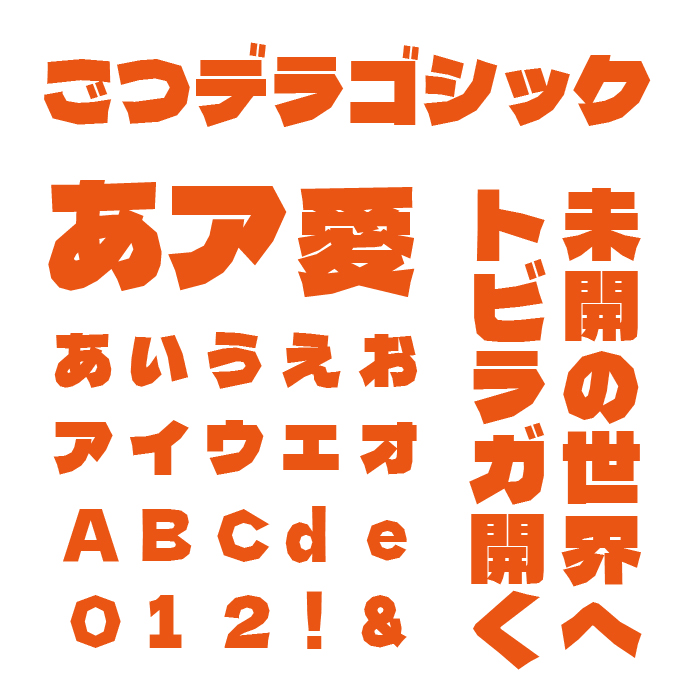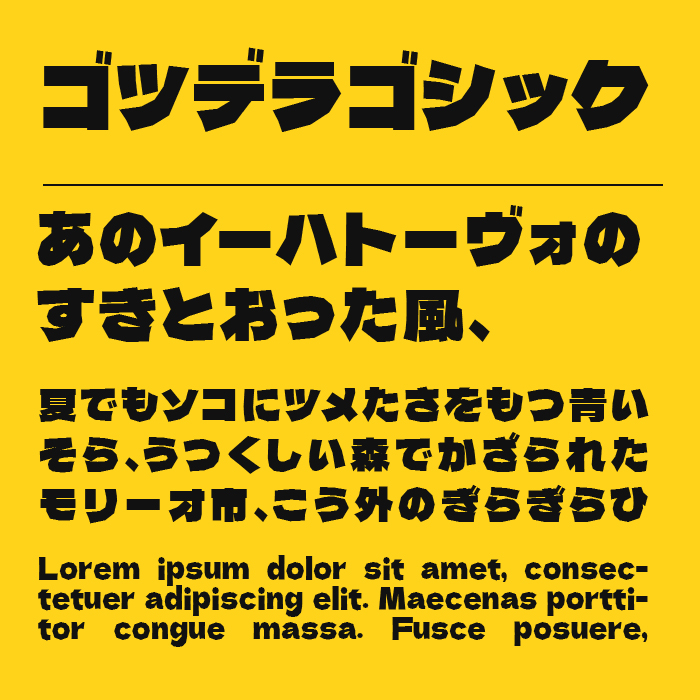
ゴツデラゴシックフォントは、その名のとおり「ごつさ」が魅力の超極太ゴシック体です。
デラゴシックフォントをベースとして、ゴツゴツになるように加工が施されています。ポップだけど。インパクトがあり力強く、メッセージを力強く届けたいときにぴったりです。
タイトルやロゴ、イベント告知など、目を引きたいとき場面などで取り入れると効果的に発揮する力強さと親しみやすさが両立しており、エンタメ系や子ども向けにもぴったりなフォントです。
収録文字は、漢字・ひらがな・カタカナ・アルファベット・数字・記号が収録。